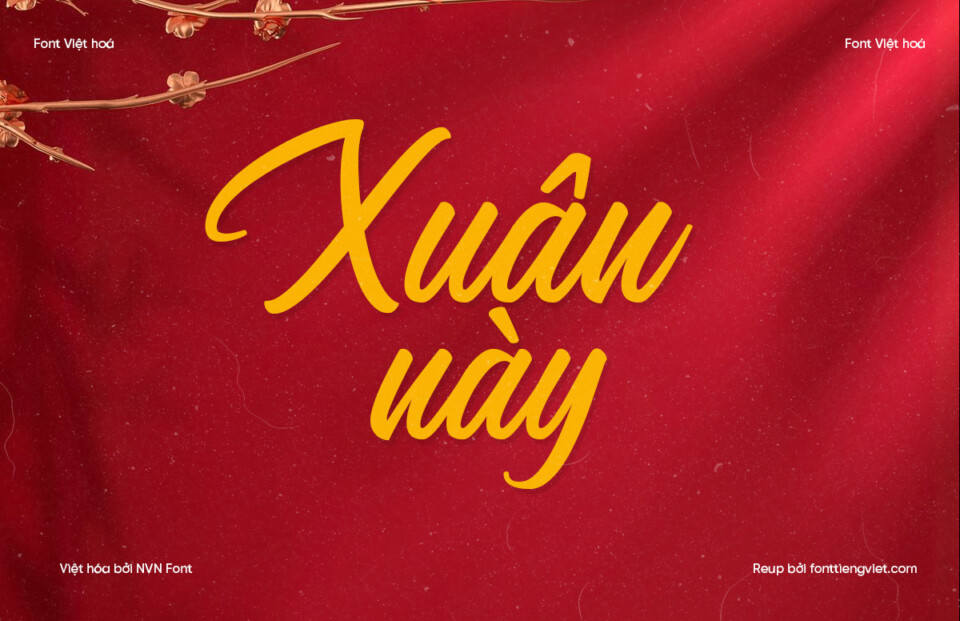
Font Việt hóa NVN Megatype Script
Font Việt hóa NVN Megatype Script – Lựa chọn hoàn hảo cho thiết kế bay bổng
Trong thế giới thiết kế đồ họa hiện đại, việc tìm kiếm một bộ Font Miễn Phí chất lượng và hỗ trợ đầy đủ tiếng Việt luôn là ưu tiên hàng đầu của các bạn học sinh, sinh viên và thầy cô giáo. Font Việt hóa NVN Megatype Script nổi lên như một giải pháp lý tưởng, mang đến vẻ đẹp mềm mại, uyển chuyển nhưng không kém phần hiện đại cho các dự án sáng tạo. Đây là một bộ font chữ dạng script (viết tay) với những đường nét thanh mảnh, uốn lượn tinh tế, giúp tạo điểm nhấn độc đáo cho mọi khung hình từ thiệp mời, bìa sách đến các bài thuyết trình học đường sinh động.
Đặc điểm nổi bật của Font Việt hóa NVN Megatype Script
Bộ font này sở hữu những đặc tính kỹ thuật ấn tượng, giúp người dùng dễ dàng làm chủ không gian thiết kế của mình. Điểm nhấn lớn nhất chính là sự kết hợp hài hòa giữa phong cách thư pháp truyền thống và xu hướng đồ họa tối giản hiện nay.
Nét chữ nghệ thuật và tính ứng dụng cao
Font Việt hóa NVN Megatype Script không chỉ đơn thuần là các ký tự đứng cạnh nhau, mà mỗi chữ cái đều được chăm chút với các đường nối mềm mại. Điều này giúp văn bản trở nên liền mạch như một bức tranh chữ viết tay thực thụ. Trong môi trường giáo dục, các em học sinh có thể sử dụng font này để thiết kế báo tường, làm thiệp chúc mừng thầy cô hoặc trang trí cho các dự án nhóm. Tính chất bay bổng của font chữ giúp truyền tải cảm xúc chân thành và sự sáng tạo không giới hạn của người sử dụng.
Khả năng hiển thị tối ưu trên nhiều nền tảng
Dù bạn sử dụng các phần mềm chuyên nghiệp như Photoshop, AI hay đơn giản là các công cụ văn phòng như Word, PowerPoint, bộ font này vẫn đảm bảo độ sắc nét cao. Quá trình Việt hóa đã được thực hiện kỹ lưỡng, đảm bảo các dấu câu tiếng Việt không bị lỗi font hay nhảy chữ, giúp văn bản luôn chuyên nghiệp và dễ đọc.
Cách sử dụng Font Việt hóa NVN Megatype Script trong học tập
Việc áp dụng font chữ nghệ thuật vào học tập không chỉ giúp bài làm đẹp hơn mà còn rèn luyện tư duy thẩm mỹ cho học sinh. Dưới đây là một số gợi ý nhỏ để bạn tận dụng tối đa vẻ đẹp của bộ font này.
Trang trí tiêu đề và làm nổi bật nội dung
Thay vì sử dụng các phông chữ mặc định khô khan, việc dùng Font Việt hóa NVN Megatype Script cho các tiêu đề chính sẽ giúp bài thuyết trình trở nên cuốn hút hơn ngay từ cái nhìn đầu tiên. Các thầy cô giáo cũng có thể sử dụng font này để soạn thảo các phiếu khen thưởng hoặc lời nhắn nhủ ấm áp gửi đến học trò, tạo nên sự gần gũi và khích lệ tinh thần học tập hiệu quả hơn.
Kết luận về bộ Font Việt hóa NVN Megatype Script